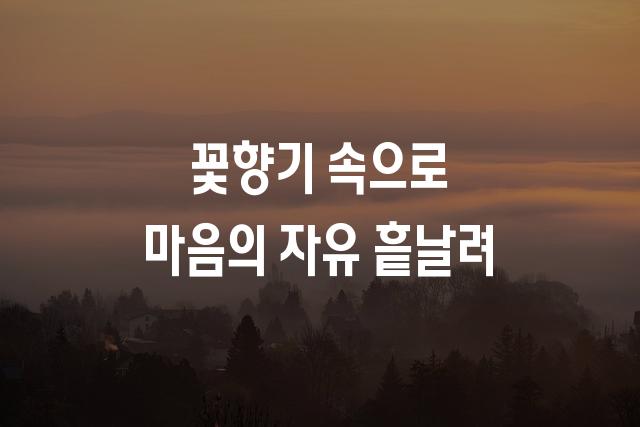
코레일체는 고딕 스타일의 기본 폰트로, 깔끔하고 명확한 읽기 경험을 제공합니다. 대중 교통 정보 전달을 위해 최적화되어, 빠르고 효율적인 커뮤니케이션이 가능합니다.
코레일체은(는)
기본 고딕, 감성적인, 부드러움 계열의 생김새를 가지고 있으며
웹/앱 디자인, 간판 등에서 자주 활용되며, 효과적인 메시지 전달에 적합합니다.
이 폰트는 기술/IT, 관광/여행 분야에 잘 어울리며,
명확한, 전문적인 느낌을 담고 있는 것이 특징입니다.